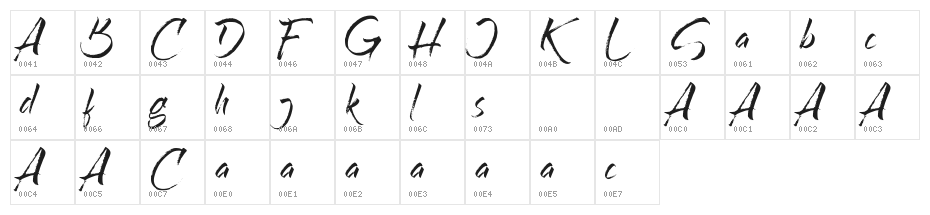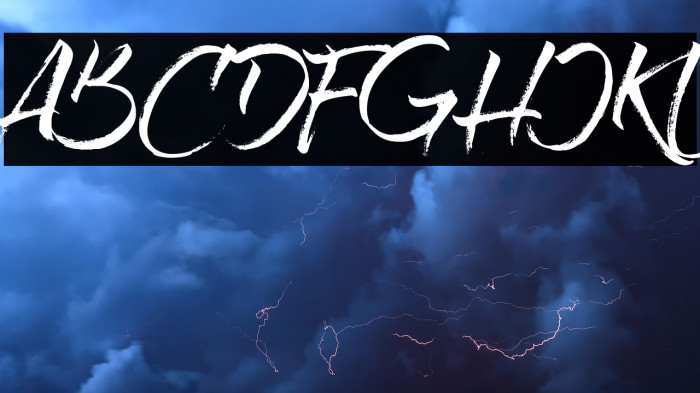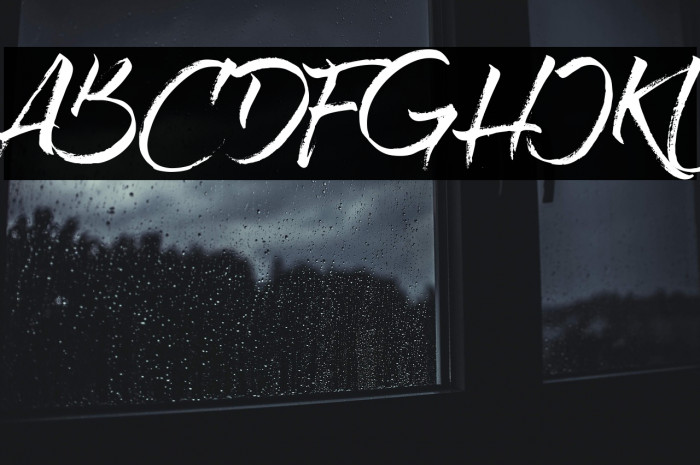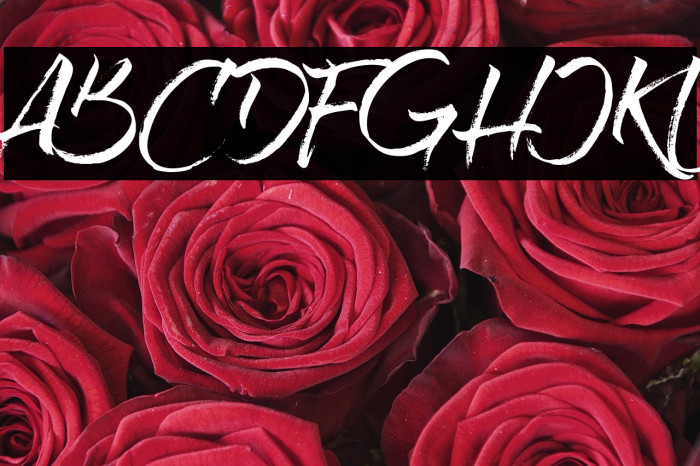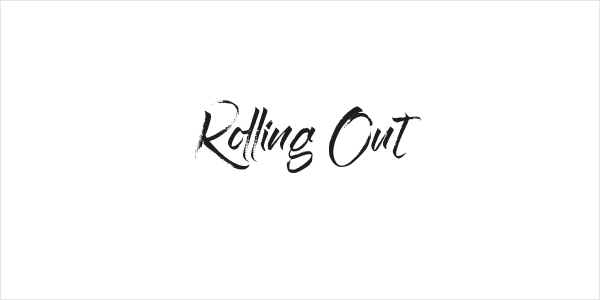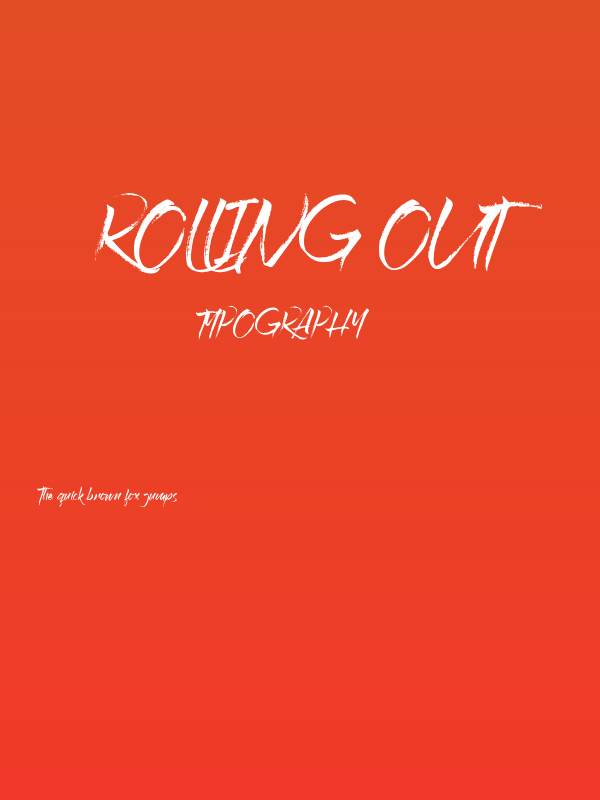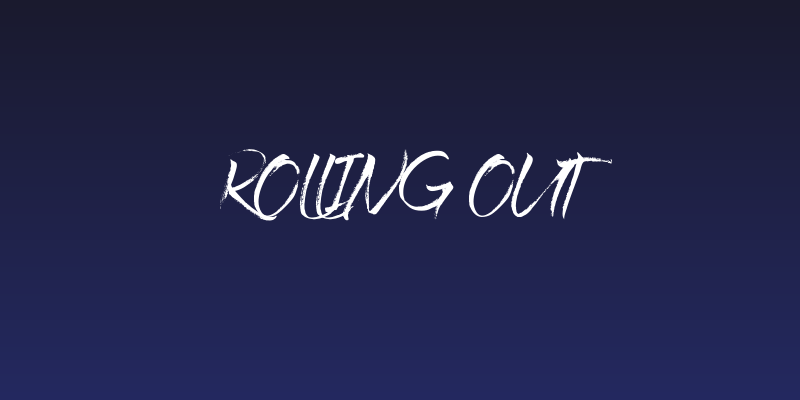
Rolling Out Font
| Anwendungsfall | Logos, Headlines, Posters |
| Vorgeschlagene Projekte | Ideal for branding, posters, invitations, and any creative project that requires a personal touch. |